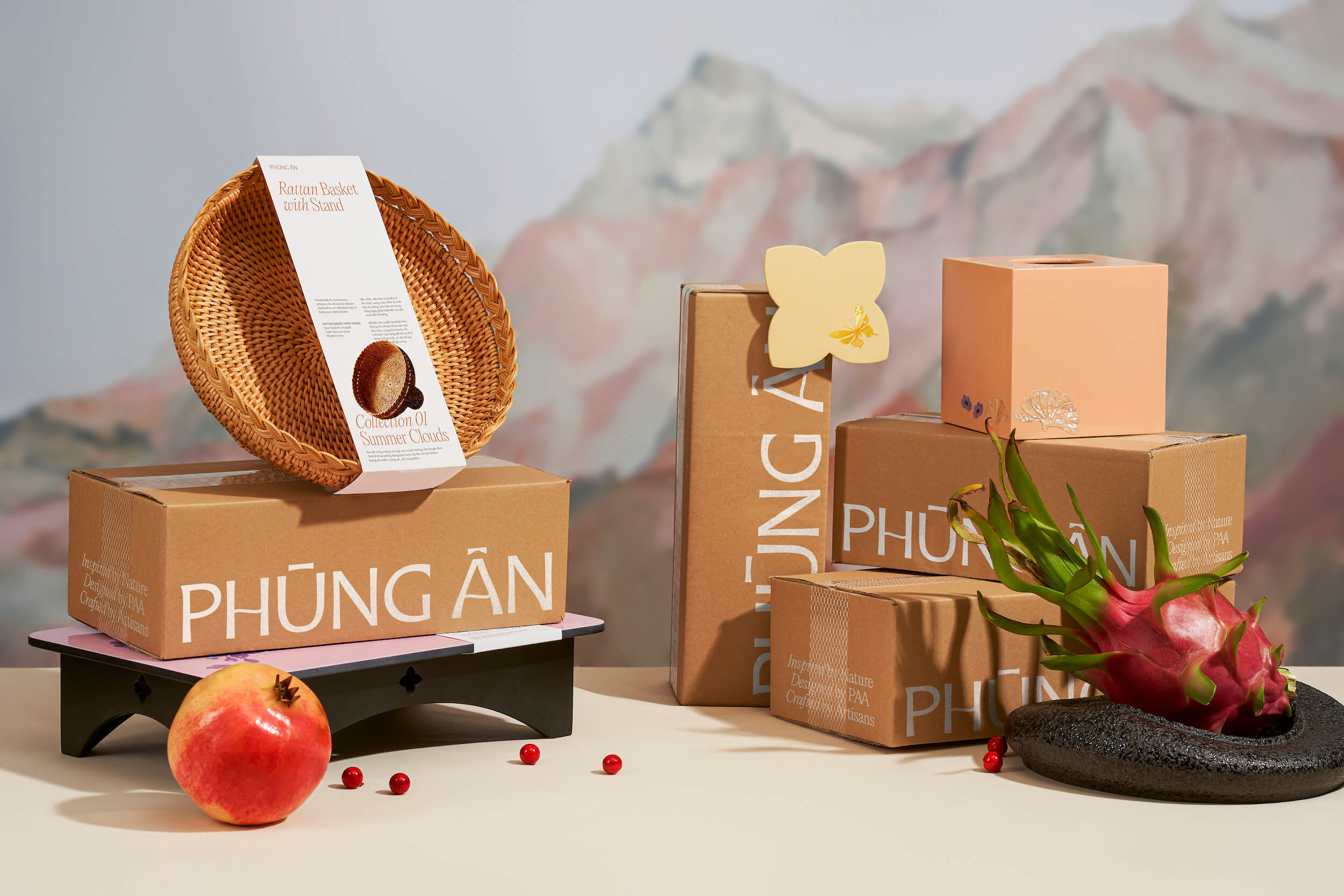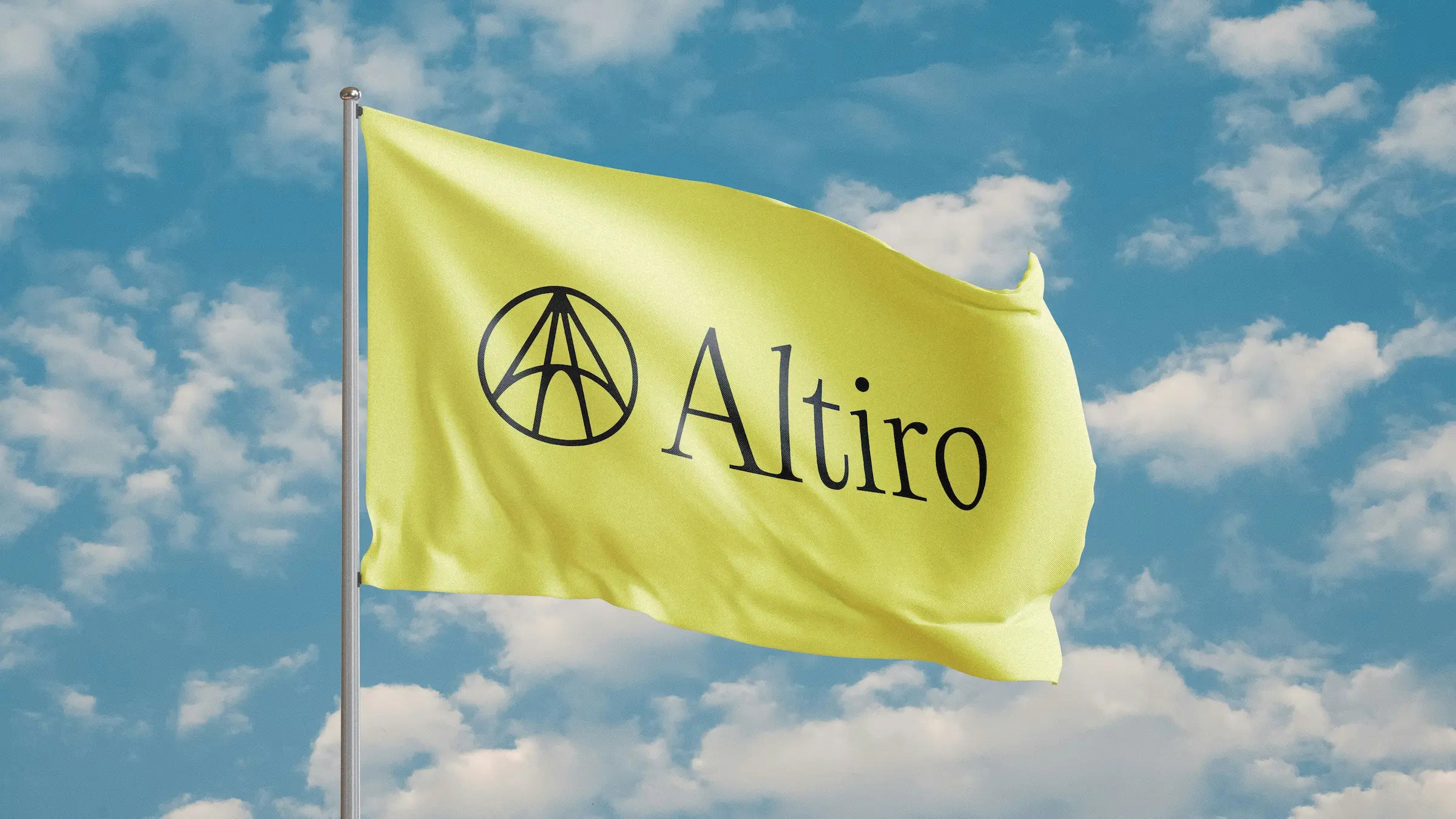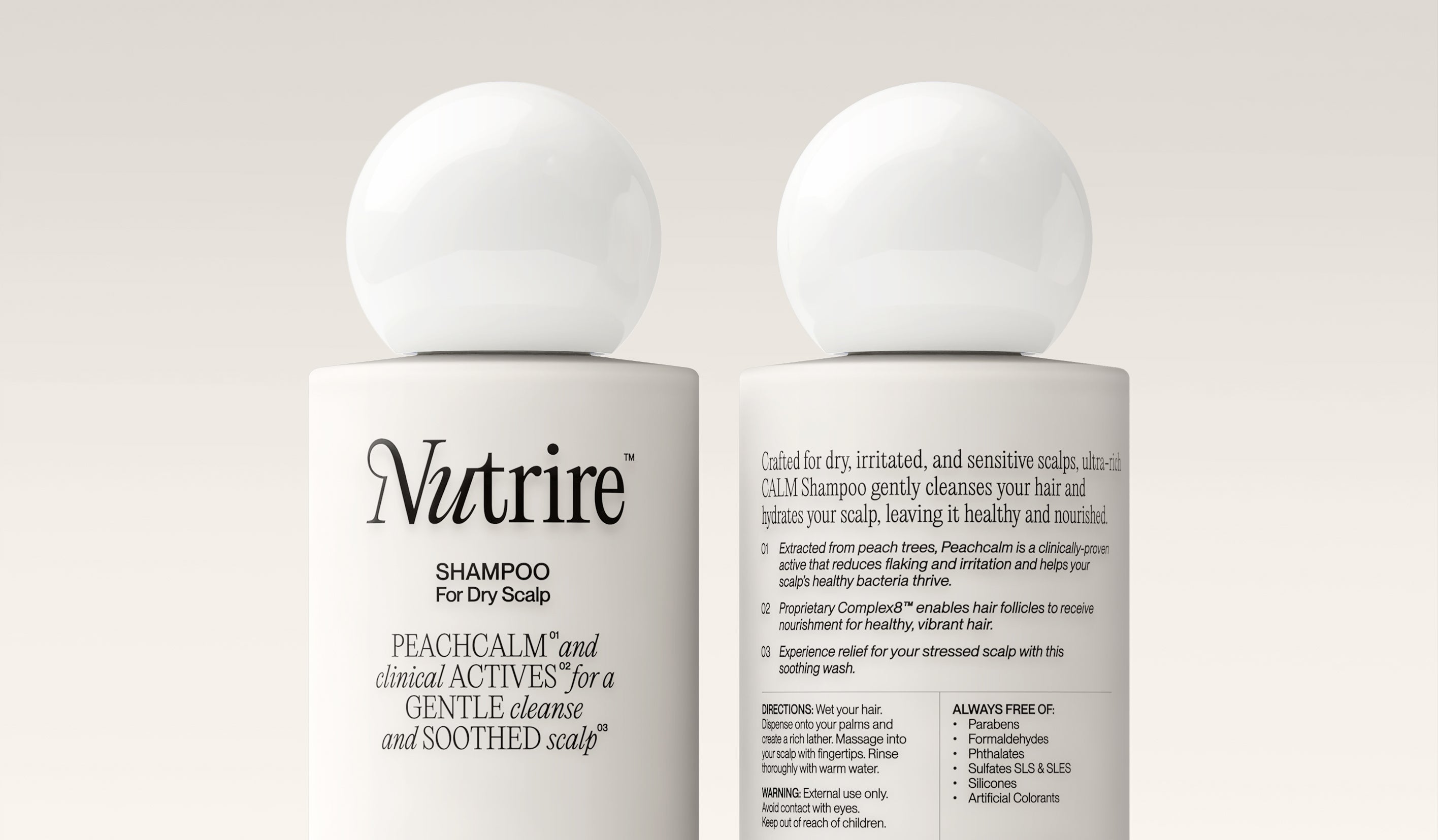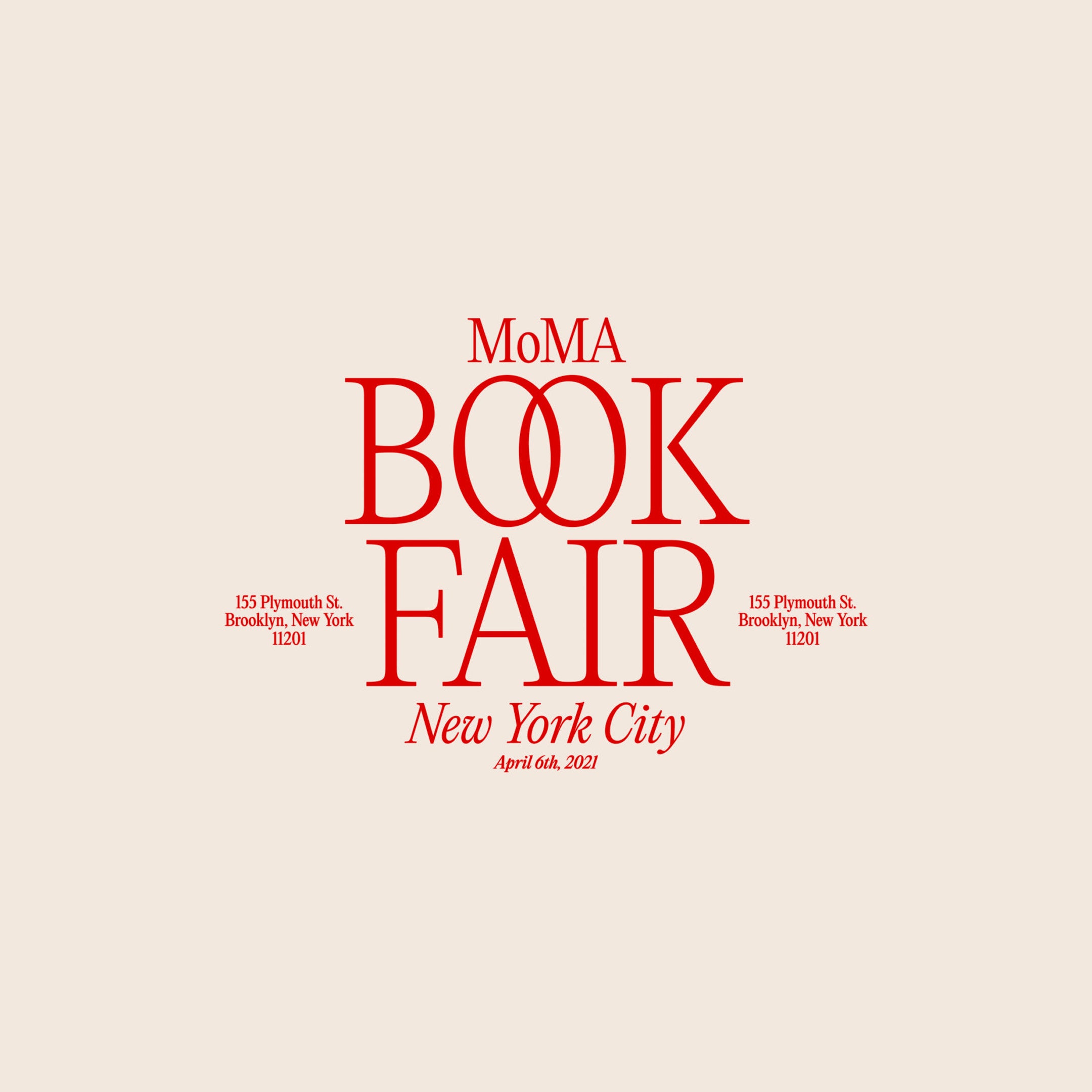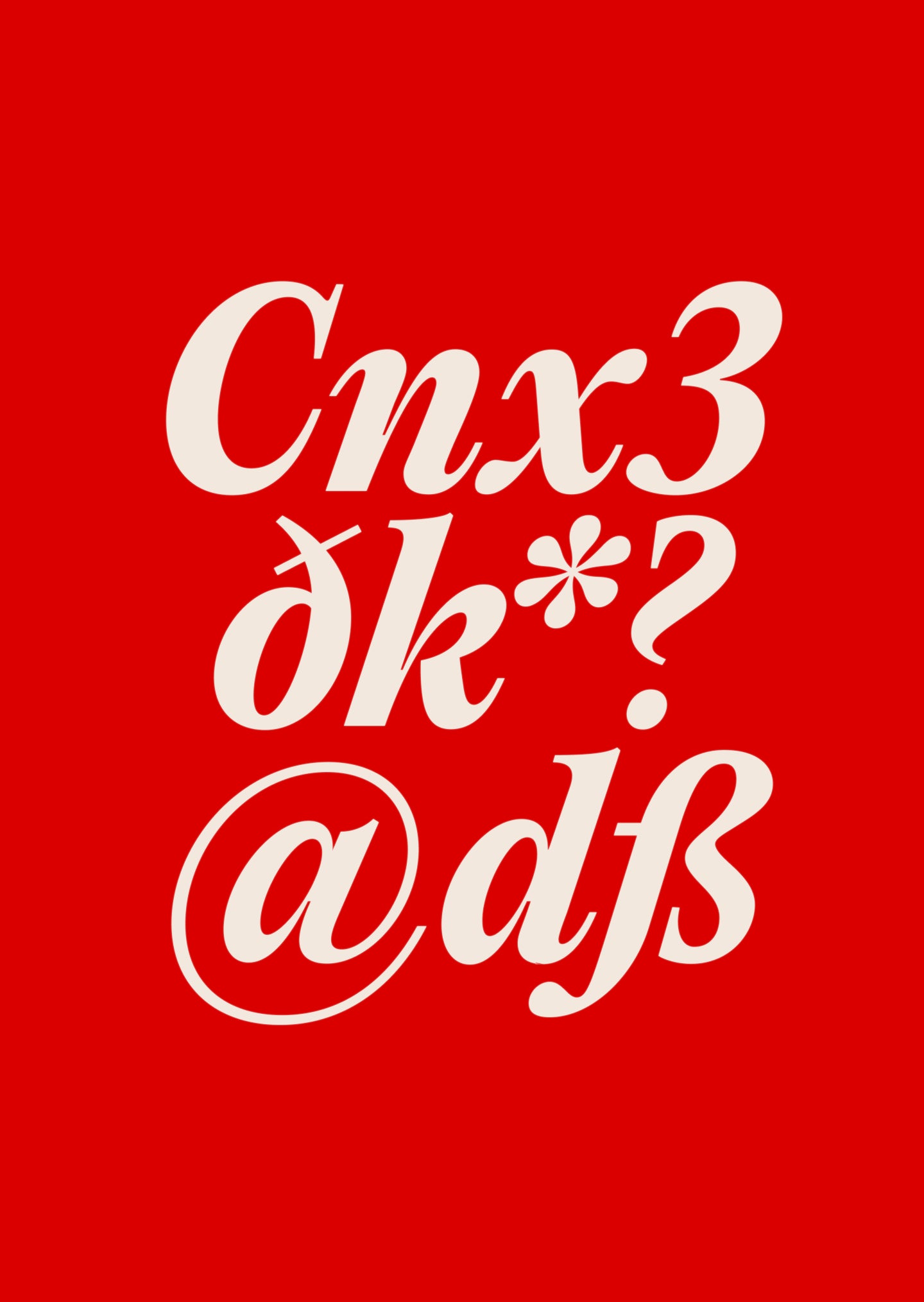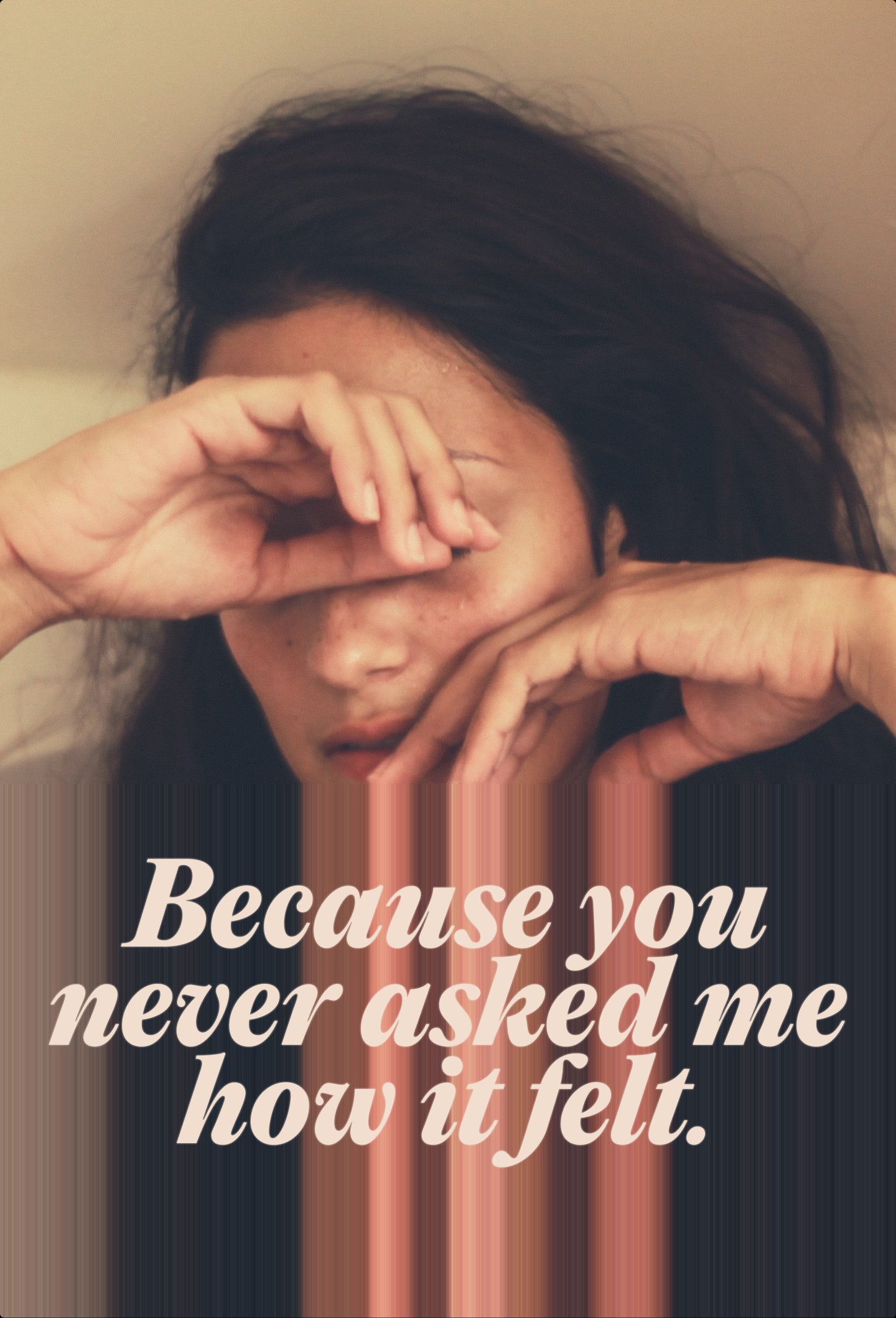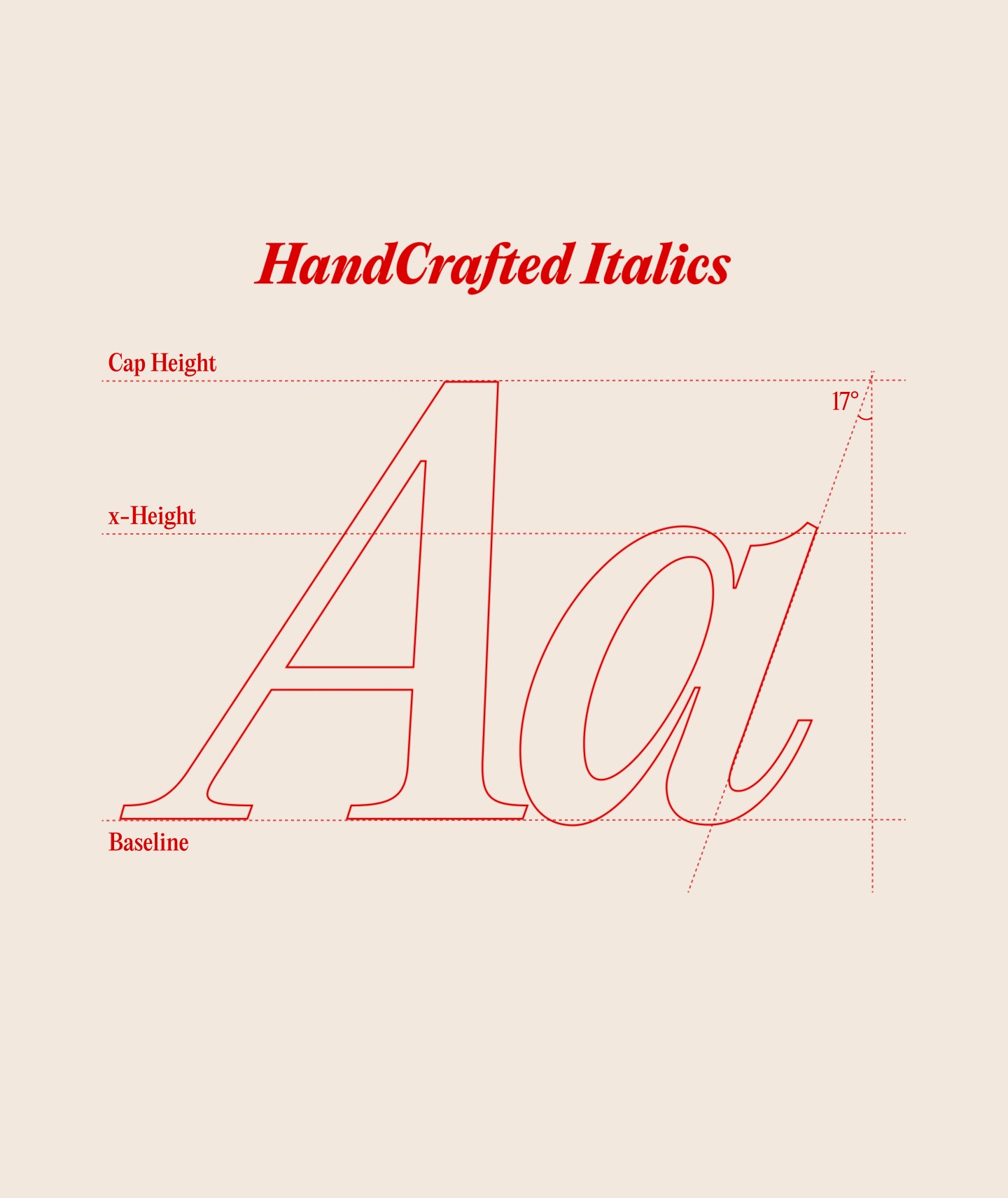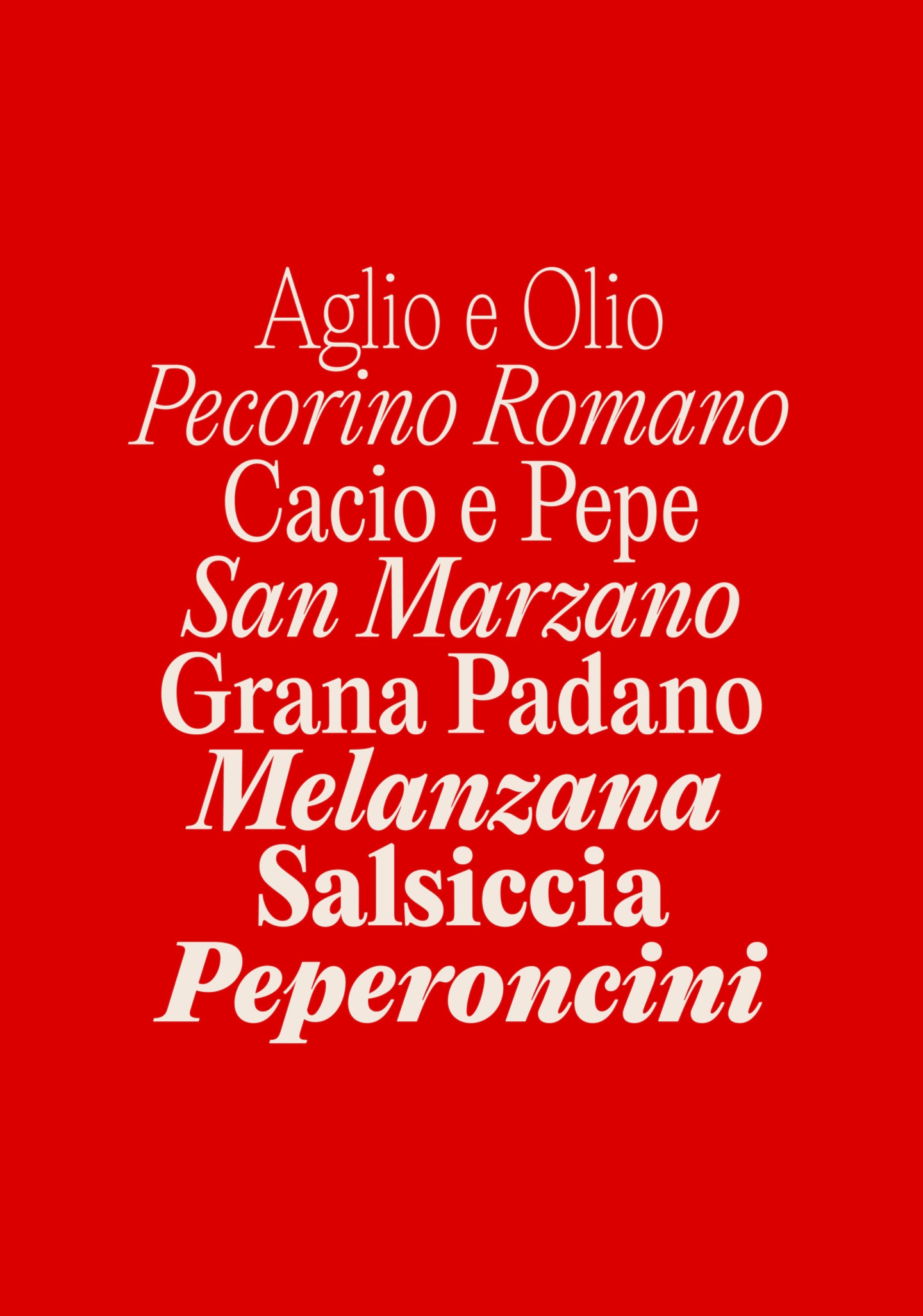
Editorial New
Elegant, refined and subtle.
Eye-catching Headlines!
Editorial New is a precise and elegant narrow serif designed with long-form content in mind—but don’t mistake its readability for restraint. This typeface carries just the right amount of flair to double as a powerful display option. Whether used in body copy or in bold, eye-catching headlines, it commands attention with effortless grace.
Perfectly suited for designs aiming to capture that nostalgic, mid-90s editorial aesthetic, Editorial New blends retro charm with a distinctly modern edge. It feels both familiar and fresh—like a vintage magazine reimagined for today’s digital canvas. In its lighter weights, it exudes a quiet sophistication: refined, subtle, and dripping with elegance. It's easy to see it gracing the pages of high-end fashion magazines or lending an air of luxury to brand identities in the beauty or design industries. But don’t be fooled—this typeface isn't just about being soft-spoken. The regular weight is a workhorse for immersive reading experiences, offering clean legibility and a steady rhythm, ideal for thoughtful editorial layouts. And when the mood shifts to bold, the heavier weights rise to the occasion. With fuller curves and heightened contrast, they become expressive and striking—just the thing for making strong typographic statements without shouting. Then there’s the italics: luscious, curvaceous, and undeniably stylish. They add a fluid, expressive dimension that elevates everything from pull quotes to callouts, infusing your design with warmth and character. Editorial New is a typographic chameleon: refined yet charismatic, versatile yet opinionated. It’s a must-try for any designer looking to strike the perfect balance between classic editorial sophistication and contemporary style.
Editorial New est variable
Editorial New
avec Italique
Fonctionnalités de Editorial New
Standard ligatures
Case sensitive forms
Élégant, raffiné et subtil.
Une police à empattement Narrow, précise et élégante, conçue pour les textes longs avec une personnalité suffisamment grande pour faire une déclaration en tant que titre. ● Elle est parfaite pour donner à votre design cette sensation rétro du milieu des années 90 tout en étant riche et contemporaine.
Dans ses graisses plus légères, Editorial New est élégant, raffiné et subtil. On l'imagine facilement utilisé dans l'industrie de la mode, pour les marques ou les magazines. ▲ Grâce à sa lisibilité précise, la graisse standard est parfaite pour les longs textes éditoriaux, mais elle est loin d'être uniforme. Elle confèrera à votre texte une touche et un style uniques.
Les poids plus lourds sont faits pour les grandes déclarations ■ Les courbes sont plus luxuriantes, un peu plus exagérées pour donner à ces poids et finalement à vos créations plus de personnalité ► Combinée aux italiques luxuriantes et courbées, cette police est un incontournable à essayer sur chaque conception.
avec Italiques